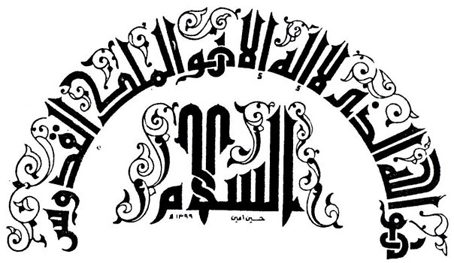
نبذه تعريفيه عن الخط الكوفي
الخط الكوفي هو من أقدم الخُطوط العربية ، ويعود أصله لعرب شمال الجزيرة العربية ؛ إذ كانوا يستخدمون خطاً يُعرف بالخط النبطي الذي ذكرناه سابقاً ، ثم تطور على مدى الزمن هذا الخط على يد أهل الحيره والأنباط وسُمي هذا الخط فيما بعد بالخط الحيري أو الأنباري ومع تقدم الزمان تغيّر اسمه وأصبح يُسمى بالخط الكوفي . اشتُهر هذا الخط في العصر العباسي والفاطمي ؛ حيث أولوه اهتماماً فائقاً وأدخلوا عليه الفنون والزخارف ، وذلك لتميزه بإمكانية كتابته على الأشكال الهندسيه الإسلاميه والزخارف مع إبقاء الحروف على قاعدتها وشكلها الأصلي . للخط الكوفي عدة أنواع منها : الخط الكوفي البسيط ، والخط الكوفي المورق ، والخط الكوفي المزهر، والخط الكوفي المضفر بالإضافة إلى الخط الكوفي المربع والخط الكوفي الهندسي
الخط الكوفي حروف والخط الكوفي الهندسي
والخط الكوفي المورق والخط الكوفي البسيط
والخط الكوفي المزخرف والخط الكوفي المربع
والعديد من الخطوط الكوفية الأكثر من رائعة
عينات من بعض أنواع الخط الكوفي المعروض للتحميل
فيما يلي صور لبعض الخطوط الكوفية الأكثر روعه على الإطلاق
وهذه الصور على سبيل المثال لا الحصر